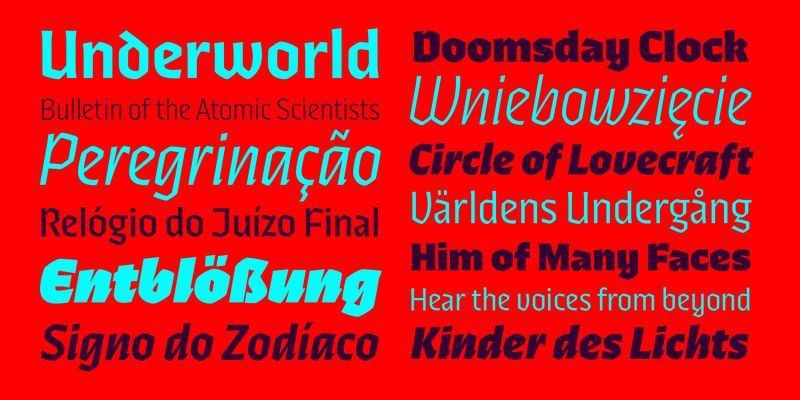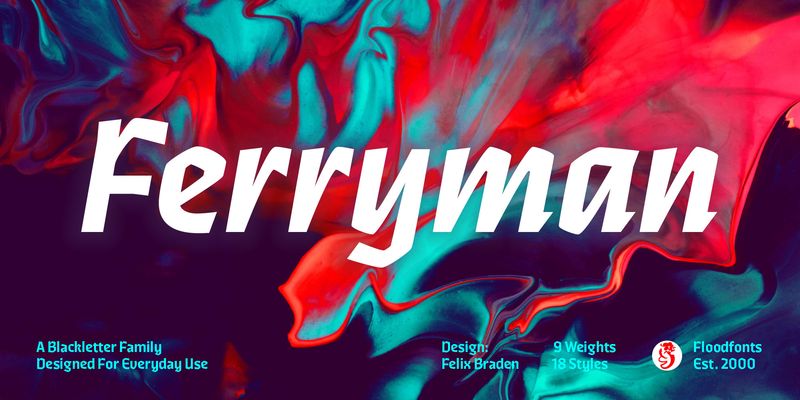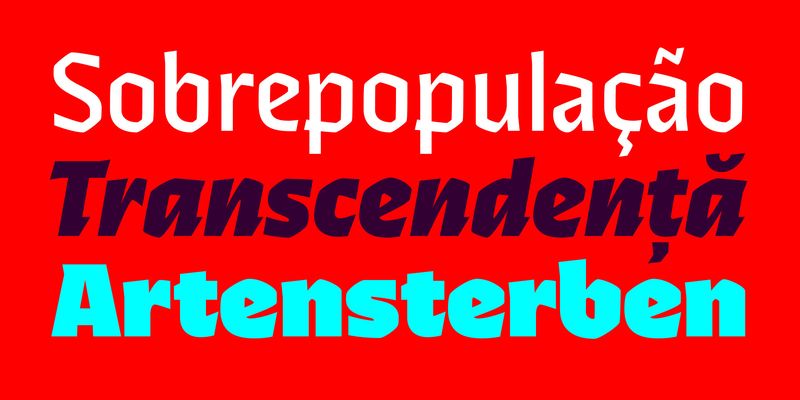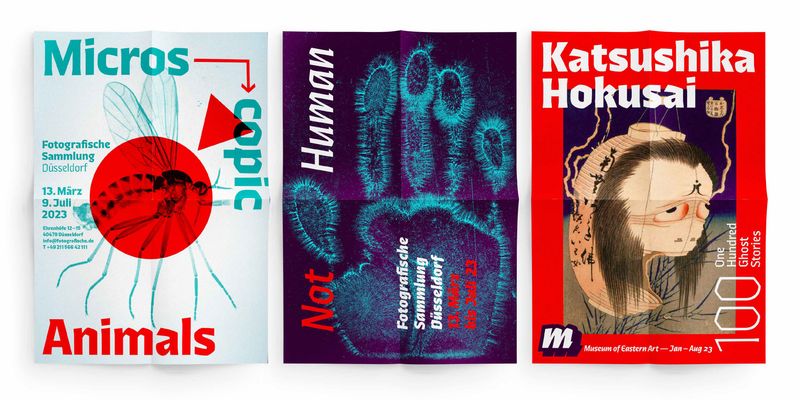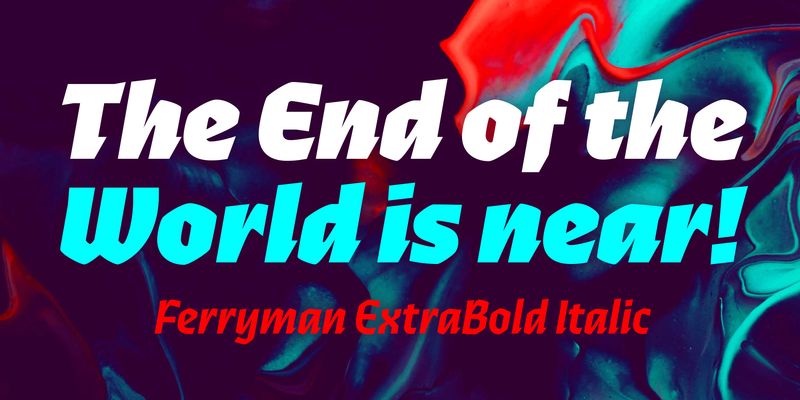
Ferryman은 현대 독자를 위한 흑체 문자 서체로 일상적인 사용을 위해 디자인되었습니다. 익숙하지 않은 흑체 문자는 적응된 라틴 문자 또는 현대의 사용자가 더 쉽게 읽을 수 있는 다른 역사적 스크립트의 문자로 대체되었습니다.
Ferryman은 남용되는 기하학 및 네오그로테스크 스타일에 대한 일종의 해독제입니다. 강한 성격을 지닌 표현력이 풍부한 디스플레이 서체로, 시각 예술, 인디 음악 및 대안적 라이프스타일 등 반문화 프로젝트 및 진보적 개념에 완벽하게 적합합니다.
아홉 종류의 두께와 각각에 상응하는 기울임꼴로 Ferryman은 다양한 창의적 가능성을 제공합니다. 각 스타일은 모든 서부, 동부 및 중부 유럽 언어를 지원하는 590개의 글리프를 제공하며 네 개의 숫자 세트와 다양한 통화 기호가 함께 제공됩니다.